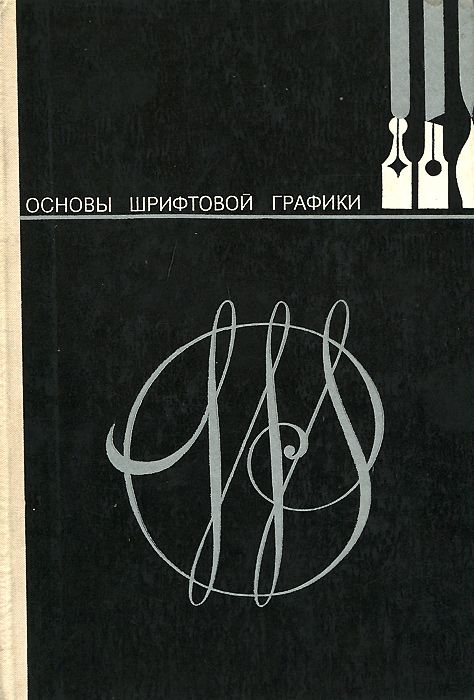
Книга «Основы шрифтовой графики» Семченко П. А., 1978 г.
В пособии излагаются основы первичных навыков и принципы построения шрифта, компоненты формальной и содержательной структуры буквы, слова и предложения. Приводятся некоторые особенности проектирования нового шрифта. Материал пособия богато иллюстрирован.